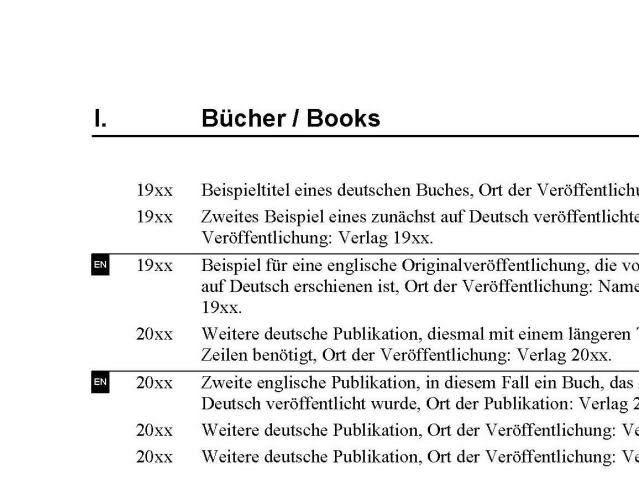
Publikationsverzeichnis
Ich bastle gerade an einem Publikationsverzeichnis. Es gibt die übliche Unterteilung zwischen "Monographie", "Herausgeberschaft" und "Artikel". Innerhalb der Rubriken wird chronologisch geordnet – mit einer schmalen Marginalspalte, in der der Publikation die Jahreszahl jeweils vorangestellt ist. So weit, so simpel.
Die Schwierigkeit ist, dass das Verzeichnis im deutsch- wie im englischsprachigen Raum gleichermaßen gut zu gebrauchen sein soll – der geneigte englische Leser soll also auf den ersten (oder spätestens zweiten) Blick sehen, welche Bücher in Englisch publiziert wurden, welche deutschen Artikel übersetzt wurden etc., ohne die ganze Liste Eintrag für Eintrag durchsuchen zu müssen.
Wenn es nicht so unüblich wäre (und Missverständnisse geradezu herausfordern würde), hätte ich große Lust, die eine Sprache in Fraktur, die andere in Antiqua zu setzen – deutliche Unterscheidung, ohne eine der Sprachen "wichtiger" erscheinen zu lassen. Kommt aber nicht ernsthaft in Frage.
Alternativ habe ich probiert, die eine Sprache aufrecht, die andere kursiv zu setzen – unterscheidet sich ganz gut, kursiv sieht aber ein bisschen nach "Auszeichnung" aus (zumal einige Buchtitel tatsächlich Kursivsetzung erfordern, was wieder zu Missverständnissen führen kann).
Dritte ausprobierte Methode: Schriftmischung. Ich habe zunächst mal frei verfügbare Serifenschriften und ihre zugehörige Sans probiert (z.B. Deja Vu), und die bewährte Minion/Myriad-Kombination. Das Ergebnis sieht eher schrecklich aus. Entweder passen die Schriften harmonisch zusammen – dann unterscheiden sie sich zu wenig. Oder man sieht einen Unterschied – dann sieht das Schriftbild aus, als wäre ein typografischer Unfall passiert.
Vielleicht hat jemand eine Idee, was man noch probieren könnte (vielleicht gibt es eine ganz andere Methode, auf die englischsprachigen Publikationen in der Liste zu verweisen).
Ach ja, das ganz muss am Ende in MS Word machbar sein ("damit's die Sekretärin immer aktuell halten kann ..."). Ich bin nicht notwendigerweise an Systemschriften oder kostenlose Schriften gebunden, wenn ich eine gute Begründung liefere, warum man etwas investieren sollte. Aber es geht hier um einen Geisteswissenschaftler – die Mittel sind also nicht üppig und eine preiswertere Lösung leichter zu "verkaufen" als eine teure.
Das Verhältnis deutsch- und englischsprachiger Schriften ist ungefähr 70/30 – falls das einen Unterschied macht ...
Ich nehme an, die meisten "Leser" des Verzeichnisses werden sich das Ding in s/w ausdrucken – Farbe wird also nicht gut funktionieren. Aber eine Art von Auszeichnung durch grafisches Element muss ich mal probieren (eine online-Version könnte ja so nette typografie.info-Smilies mit wehender Fahne haben ... well, just kiddin', of course ... :D )
die jahreszahl entweder der englischsprachig verfügbaren oder der nur deutsch vorhandenen schriften fett setzen? oder ein symbol (pfeil?) davorsetzen?
Oder mit einer Spalte mit Landesfahnen? :?
Damit stößt man aber immer jemanden vor den Kopf – im Zweifelsfall Liechtensteiner oder Neuseeländer. Die englische Fahne kennt außer Fußballfans (und Engländern) übrigens niemand.
Da hier immer alle so normenverrückt sind, wundert es mich ein wenig, dass noch niemand die ISO-Codes DE und EN vorgeschlagen hat. Wenn’s kürzer sein soll, gingen ja auch D und E, zwischen Jahreszahl und Titel oder an den rechten Rand.
Fraktur ist doch super.
Ansonsten könntest Du einen Stern (*) an die englischen Werke setzen, und unter die Überschrift des Verzeichnisses eine Erklärung, etwa so:
* in englischer Sprache
Sind die einzelnen Einträge nummeriert? Wenn ja dann würde ich den Nummer Farben zuweisen. Wenn die Nummern in eckigen Klammern stehen kann man auch nur den Klammern die Farben zuweisen. Das stört die Formatierung der eigentlichen Einträge überhaupt nicht, sollte aber deutlich genug sein um die sofortige Identifizierung zu ermöglichen (es muß natürlich ein Schlüssel vorhanden sein, der die Farben erklärt; entweder in einer Fußnote oder gleich zu Beginn des Verzeichnisses).
Oder mit einer Spalte mit Landesfahnen? :?
Damit stößt man aber immer jemanden vor den Kopf – im Zweifelsfall Liechtensteiner oder Neuseeländer.
Meinst Du? Man sieht solche kleinen Fähnchen schließlich auch oft auf Websites, die in mehreren Sprachen zur Verfügung stehen ... :? Mich hats jedenfalls noch nie gestört, wenn (beispielsweise auf einer österreichischen Website) der Link zur deutschen Variante ne österreichische Fahne war :?
Die englische Fahne kennt außer Fußballfans (und Engländern) übrigens niemand.
:o Meinst Du St George's Cross oder den Union Jack ...? In jedem Fall solltest Du Dich mal öfter unter gebildete und kultivierte Leute begeben ... ;) ;)
Da hier immer alle so normenverrückt sind, wundert es mich ein wenig, dass noch niemand die ISO-Codes DE und EN vorgeschlagen hat. Wenn’s kürzer sein soll, gingen ja auch D und E, zwischen Jahreszahl und Titel oder an den rechten Rand.
Nicht ganz so auffällig, aber schön normgerecht ... ;)
Oder mit einer Spalte mit Landesfahnen? :?
Damit stößt man aber immer jemanden vor den Kopf – im Zweifelsfall Liechtensteiner oder Neuseeländer.
Meinst Du? Man sieht solche kleinen Fähnchen schließlich auch oft auf Websites, die in mehreren Sprachen zur Verfügung stehen ... :? Mich hats jedenfalls noch nie gestört, wenn (beispielsweise auf einer österreichischen Website) der Link zur deutschen Variante ne österreichische Fahne war :?
Fähnchenicons gehören zum Web der 90er Jahre (so wie animierte Bullets). Auf modernen, professionell gestalteten Websites sieht man sie kaum noch.
In sehr eng umgrenzten Anwendungen mag ihre Anwendung gerade noch OK sein, z.B. bei einer zweisprachigen Website von Görlitz/Zgorzelec, da dort die 1:1-Beziehung Sprache–Staat halbwegs klar ist. Aber gerade auf Websites, auf denen die Sprecher einer bestimmten Sprache angesprochen werden – und nicht die eines bestimmten Staates – haben Fähnchen nichts verloren. Bei der Weltsprache Englisch ist das besonders eklatant. Vermeintliche Kompromisslösungen wie icon-english-flag.gif sind doch einfach nur abscheulich. Aber selbst bei anderen Sprachen gibt’s unlösbare Probleme. Spanische Flaggen wirkten auf den Websites von US-Städten mit vielen Spanischsprechern völlig deplatziert. Gerade war ich auf einer israelischen Website, die in Hebräisch, Arabisch, Russisch und Englisch angeboten wurde. Welche Flagge sollte für Arabisch herhalten? Die palästinensische? Die saudiarabische? Und für Russisch? Immerhin kommen die russischsprachigen Einwanderer aus der gesamten Ex-Sowjetunion. Dann lieber die sowjetische? Selbst die eigentlich offensichtliche Verwendung der israelischen Flagge für den hebräischen Teil verbietet sich, weil sie die vollwertige Staatsbürgerschaft der Arabischsprecher implizit in Frage stellt.
Die englische Fahne kennt außer Fußballfans (und Engländern) übrigens niemand.
:o Meinst Du St George's Cross oder den Union Jack ...?
Kontext, lieber Kollege! Durch den Verweis auf den Fußball sollte eigentlich klar sein, welche gemeint war.
Und welche Lösung empfindest Du als besser (Website)? Klar kann ich Sachen abfragen wie IP und eventuell Spracheinstellungen(?), und dann die Seite in der wahrscheinlichsten Sprache aufrufen, aber das ist noch lang keine sichere Lösung. Bei einem Unternehmen in dem ich früher tätig war stand das Rechenzentrum offensichtlich in den Niederlanden, was beim Aufrufen von Websites öfters recht nervig war ... Und wie kennzeichne ich jetzt einen einigermaßen universell verständlichen Link zum auswählen einer anderen Sprache ...? :?
:o Meinst Du St George's Cross oder den Union Jack ...?
Kontext, lieber Kollege! Durch den Verweis auf den Fußball sollte eigentlich klar sein, welche gemeint war.
Als ob ich was vom Fußball wüsste ... Aber im Ernst, wer kennt St George's Cross nicht ...!? :?
Noch ’ne Idee: wie wär’s mit einer dreispaltigen Lösung? Links die Jahreszahlen der Veröffentlichungen in der einen Sprache, rechts die in der anderen, dazwischen die Namen der Veröffentlichungen. Ungefähr so:
published in Englisch????????????????????????????????auf Deutsch veröffentlicht
1999????????????????Die Geschichte der …
???????????????????? The History of …????????????????2000
Textlinks!
Okay ... Aber erstens bist Du – ich setze das jetzt mal voraus – ein sehr versierter Websurfer und auch mehr oder weniger technikaffin, das kann man heutzutage wo immer mehr Menschen einen Internetzugang nutzen eher nicht mehr voraussetzen. Und gerade bei einer Website die nicht privat betrieben wird, beispielsweise einer Firmenwebsite, sollte man die Barriere so niedrig wie möglich halten. Und zweitens muss ein Textlink immer in irgendeiner Sprache verfasst sein. Wenn ich jetzt herausfinde dass mein Besucher anscheinend in Italien sitzt, und ich ihm zunächst die ganze Seite in italienischer Sprache präsentiere, in welcher verfasse ich dann diesen Link? Schreibe ich »tedesco« oder »inglese«? »german/english«? »deutsch/englisch«? In jedem Fall wieder ein hohes Risiko, genau eine Sprache zu erwischen, die der Besucher nicht beherrscht ... Da ist ein Icon schon etwas universeller, oder?
Und welche Lösung empfindest Du als besser (Website)? Klar kann ich Sachen abfragen wie IP und eventuell Spracheinstellungen(?), und dann die Seite in der wahrscheinlichsten Sprache aufrufen, aber das ist noch lang keine sichere Lösung.
Erkennung per IP-Adresse ist in der Tat unsicher (und aufwändig). Das also nicht.
Aber die Spracheinstellung des Browsers zu berücksichtigen, ist einfach höflich. Dazu ist die Spracheinstellung des Browsers schließlich vorgesehen. Aber zusätzlich muss immer die Möglichkeit bestehen, die Sprache zu ändern (schließlich bringt es mir nichts, wenn ich als ausschließlich englischsprachiger Tourist in ein Berliner Internetcafé komme und auf dem deutschen Computer dann nur deutschsprachige Infos sehe). Und die manuelle Auswahl der Sprache funktioniert am besten per …
Textlinks!
Wenn ich auf einer ausländischen Seite bin, suche ich gar nicht erst nach Flaggen oder der möglichen Position einer Sprachauswahl. Ich drücke Befehl+F und suche nach »english« etc.
:rockon:
Wenn ich jetzt herausfinde dass mein Besucher anscheinend in Italien sitzt, und ich ihm zunächst die ganze Seite in italienischer Sprache präsentiere, in welcher verfasse ich dann diesen Link?
Immer in der Zielsprache, also z.B.
?[Deutsch] [Englisch] [polski] [magyar] [??-??????]
Es macht doch nichts, wenn der Besucher ??-?????? nicht versteht – dann versteht er den Inhalt der dort verlinkten Seite doch auch nicht! Oder hattest du schon mal Probleme zu verstehen, worum es im unteren Teil der linken Spalte dieser Website geht: http://de.wikipedia.org/?
Aber zusätzlich muss immer die Möglichkeit bestehen, die Sprache zu ändern (schließlich bringt es mir nichts, wenn ich als ausschließlich englischsprachiger Tourist in ein Berliner Internetcafé komme und auf dem deutschen Computer dann nur deutschsprachige Infos sehe).
Genau, das ist was ich meine :D
[Einen Link zur Sprachauswahl] immer in der Zielsprache, also z.B.
?[Deutsch] [Englisch] [polski] [magyar] [??-??????]
Das klingt zunächst auch sehr sinnvoll, keine Frage :D Aber wie löst Du das bei einem größeren Unternehmen mit Seitenbesuchern aus aller Herren Länder? Die Seite irgendwo mit Textlinks zupflastern? Nur einen, der dann möglicherweise wieder in der falschen Sprache ist? Oder doch vielleicht lieber ne kleine Fahne, die beim hovern ein kleines Menü mit weiteren Fahnen öffnet ...? :?
Bei zu vielen Links kann man ja eine Dropdown-Liste machen.
Schon :D Aber wie machst Du das kenntlich? »Language«? »Sprache«? Dazu müsste man ja wieder die Sprache beherrschen, in der der Name des Menüs verfasst ist ... :?
Vielen Dank für eure Vorschläge.
Die Versionen mit fett gesetzten Jahreszahlen und Sternchen probiere ich in jedem Fall aus – eine simple Unterscheidung, ohne dass die Einträge selbst hervorgehoben und irgendwie in eine Hierarchie gebracht werden. Die Version mit drei Spalten gefällt mir spontan sehr gut; mal sehen, ob sich das gut umsetzen lässt. Bei der Farbversion bin ich immer noch skeptisch; die meisten werden sich die Liste wohl als s/w-Ausdruck anschauen und kaum noch einen Unterschied sehen.
... und damit zurück zur Website-Sprachdiskussion :D
Wenn Du bei der dreispaltigen Variante zu einer ansehnlichen Lösung findest, dann zeig die doch mal hier rum :D Ich fand den Gedanken auch ansprechend, bin aber bei einem kurzen, halbherzigen InDesignmassaker nicht zu etwas gekommen, was mir in der Praxis so gut gefallen hätte wie in der Theorie :D
Und mir fällt gerade ein weiteres Problem auf: Im Publikationsverzeichnis gibt es natürlich auch Übersetzungen in andere Sprachen als Englisch – Russisch, Spanisch, Polnisch, Koreanisch, Französisch. Die Zahl ist insgesamt eher gering, aber irgendwie möchte ich diesen Sprachen auch gerecht werden.
Man könnte natürlich alle in einer nicht-deutschsprachigen Rubrik zusammenfassen (und so am dreispaltigen Layout festhalten); da die meisten Titel in dieser Rubrik tatsächlich englisch sind, kann sich der englischsprachige Leser daran noch immer orientieren (und muss nur die Einträge "mit den komischen Schriftzeichen" ignorieren ...).
Vielleicht spricht die Vielsprachigkeit aber doch für EN-, RU-, DE-, ...-Kürzel.
Bei zu vielen Links kann man ja eine Dropdown-Liste machen.
Da haste aber wieder das Problem, dass die Einträge nicht per Suchfunktion gefunden werden. Und wenn im ersten Eintrag was unverständliches steht, steckt der Besucher schnell in einer Sackgasse. Dann schon lieber eine lange Latte mit ISO-Sprachencodes, so wie die EU das macht.
Wenn’s ein bisschen mehr Aufwand sein darf und die Sprachenliste so lang ist, dass eine sequentielle statische Auflistung wirklich jeden Rahmen sprengt, kann ich mir auch Formen wie in einer tag cloud vorstellen, bei der die am häufigsten nachgefragten Sprachen am größten dargestellt werden. Der Vorteil sollte hier sein, dass das auch die bekanntesten Sprachnahmen sein sollten, so dass selbst Nicht-Sprecher erkennen sollten, dass es sich hier um eine Sprachauswahlfunktion handelt.
Ist noch mehr Aufwand erlaubt und darf ECMAScript (a.k.a. JavaScript) ins Spiel kommen, ginge auch eine scrollbare Auswahlliste, die automatisch scrollt, wenn man mit der Maus drüber fährt.
Schon :D Aber wie machst Du das kenntlich? »Language«? »Sprache«? Dazu müsste man ja wieder die Sprache beherrschen, in der der Name des Menüs verfasst ist ... :?
Da gibt’s doch gestalterische Möglichkeiten: ’ne Collage aus jeweils markanten lateinischen, kyrillischen, arabischen, hebräischen Buchstaben/asiatischen Zeichen oder von mir aus auch ’ne Weltkugel.
Ich habe die dreispaltige Variante ausprobiert und bin leider auch zu keinem ansehnlichen Ergebnis gekommen. Ich bekomme einfach keine ruhige rechte Kante in der Publikationenspalte hin – entweder sieht es ausgefranst aus, oder man muss die Spalte so eng machen, dass es schon wieder Platzverschwendung ist.
Was haltet ihr von dieser Version mit kleinen EN-"Fähnchen"? Im Detail ist noch nichts abgestimmt, nur grundsätzlich ...
Durch die Striche sieht es aus, als würde das Verzeichnis in mehrere Blöcke geteilt werden.